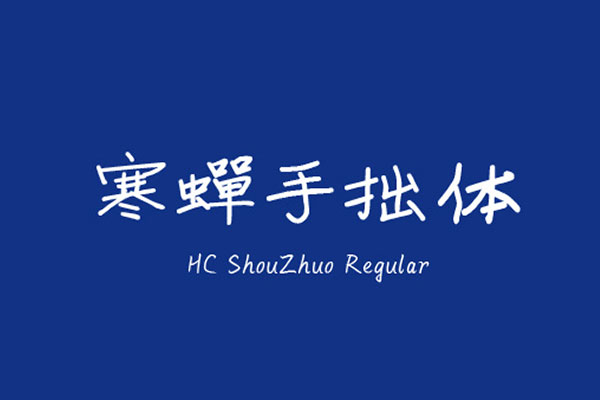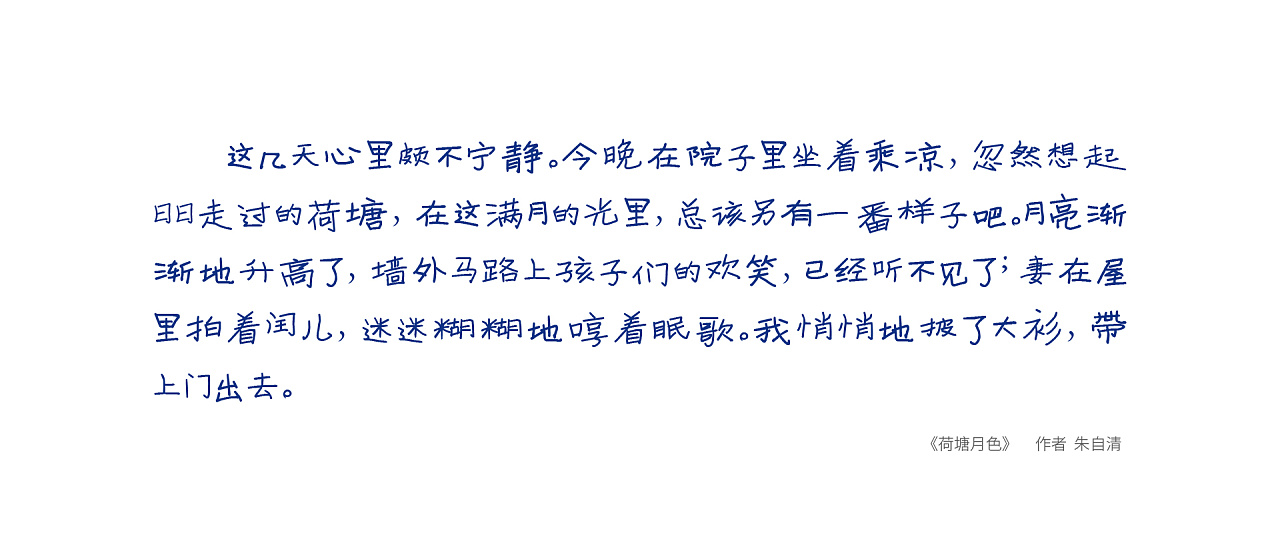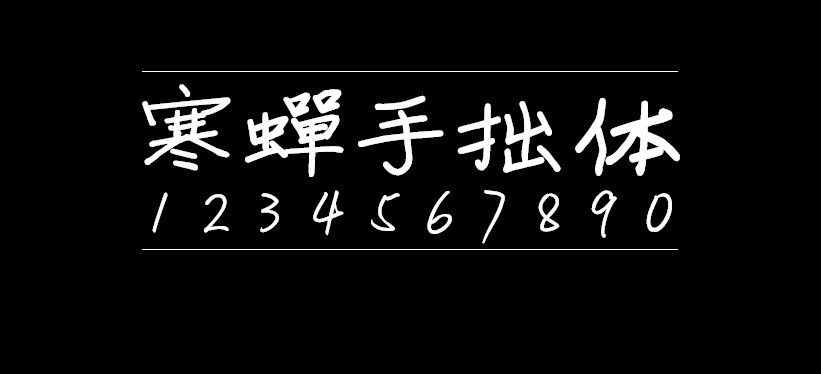
寒蝉手拙体
寒蝉手拙体是深圳设计师Siue创作的字体,主要精髓为发掘手写字体的手拙之美,字体给人一种逼真手写的视觉体验。虽应用范围有限,但有其不可替代和独特的价值。以创造的笔意和结构完成,形成风格独特的一套小众字体。本字体基于中华人民共和国GB2312-80字符集标准,共收容字形7586个(包含简体和繁体)。使用范围:免费授权全社会使用(包括商用)。